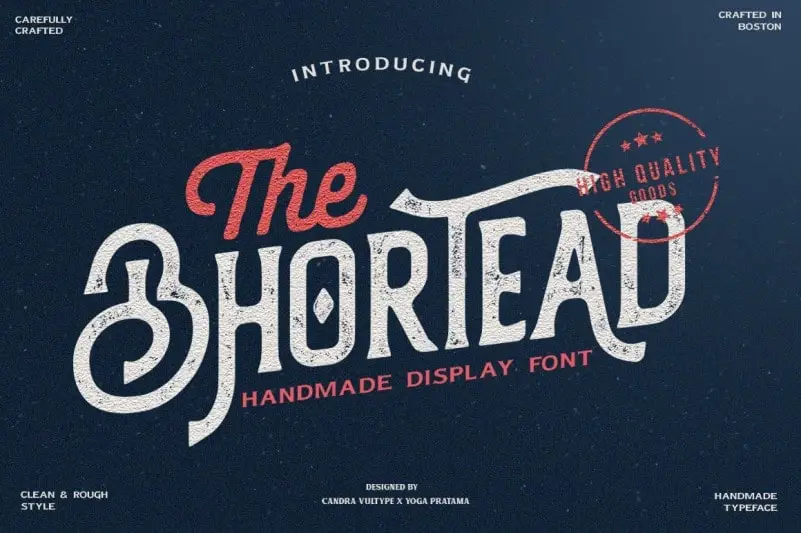
The Bhortead Display Font – Download Grátis
A fonte ‘The Bhortead Display Font’ é inspirada nas belas designs vintage fabricadas pela Vultype, conhecida por suas linhas simples e deslizantes. Esta fonte traz um toque único que combina a elegância dos designes clássicos com uma aparência áspera e viva. O Clean Style oferece linhas levemente retas, ideal para ambientes mais formais ou ressalvas, enquanto o Rough Style apresenta linhas grossas e incisivas, adequado para criações mais impactantes e modernas. Além disso, a fonte dispõe de várias características em formato OpenType que permitem combinar as diferentes estilos juntos para criar um design ainda mais dinâmico e vibrante. Seja para criar uma marca memorável ou simplesmente adicionar o toque final à sua próxima criação visual, ‘The Bhortead Display Font’ oferece um lembrete de nostalgia, misturando os elementos arquitetônicos dos anos 1900 com a modernidade da tecnologia atual.